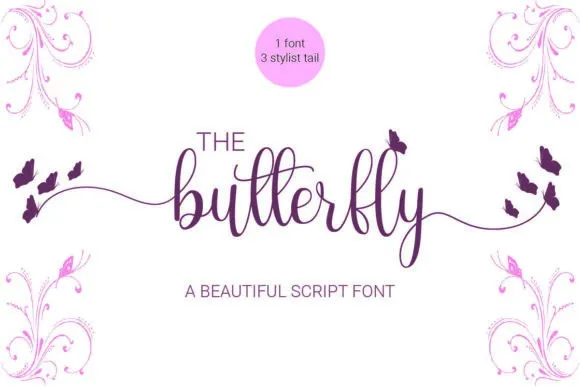
The Butterfly Calligraphy Font – Download Grátis
A Butterfly Calligraphy Font é uma elegante tipografia feminina que combina detalhes finos para criar um estilo luxuoso e sofisticado. Desenvolvida pelo designer de fontes esforçype, essa fonte é perfeita para aqueles que buscam dar um toque especial a qualquer ideia de design. Seja em cartões de aniversário delicados, rótulos de chá exquisitos ou até mesmo em uma logo cuidadosamente personalizado, a Butterfly Calligraphy Font oferece a oportunidade de adicionar aquela nota mágica e encantadora que torna cada projeto único e especial. Composta por linhas delicadas e traços suaves, essa fonte é ideal para aqueles que buscam expressar emoções e sentimentos através do design gráfico, adicionando um toque autêntico e refinado a qualquer projeto visual.